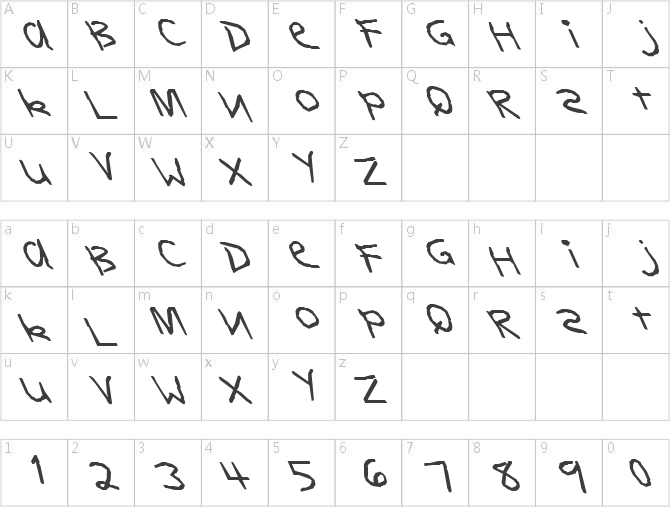
字體名稱: FZ HAND
FZ HAND 11 LEFTY
FZ HAND 11 LEFTY介紹
FZ HAND 11 LEFTY字體字庫是一款讓人賞心悅目、百看不厭的英文字體,適合各類廣告和產品包裝設計應用,字體大小0.03MB,格式為ttf字體,上傳用戶是小籃子,作者/版權方為未知
FZ HAND 11 LEFTY效果圖